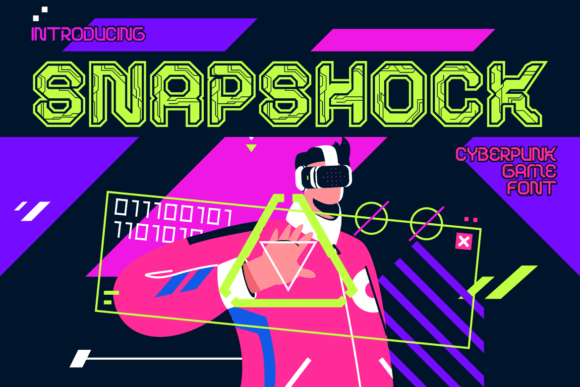
Snapshock
หากคุณกำลังมองหาเนื้อหาคุณภาพสูงเช่น Snapshock แพ็คเกจพรีเมียมนี้เป็นตัวเลือกที่ยอดเยี่ยมสำหรับโปรเจ็กต์สร้างสรรค์ของคุณ
สร้างขึ้นอย่างแม่นยำ Snapshock ให้เวกเตอร์ที่สะอาด พิมพ์ตัวอักษรที่ราบรื่น และใบอนุญาตเชิงพาณิชย์เพื่อความสบายใจ